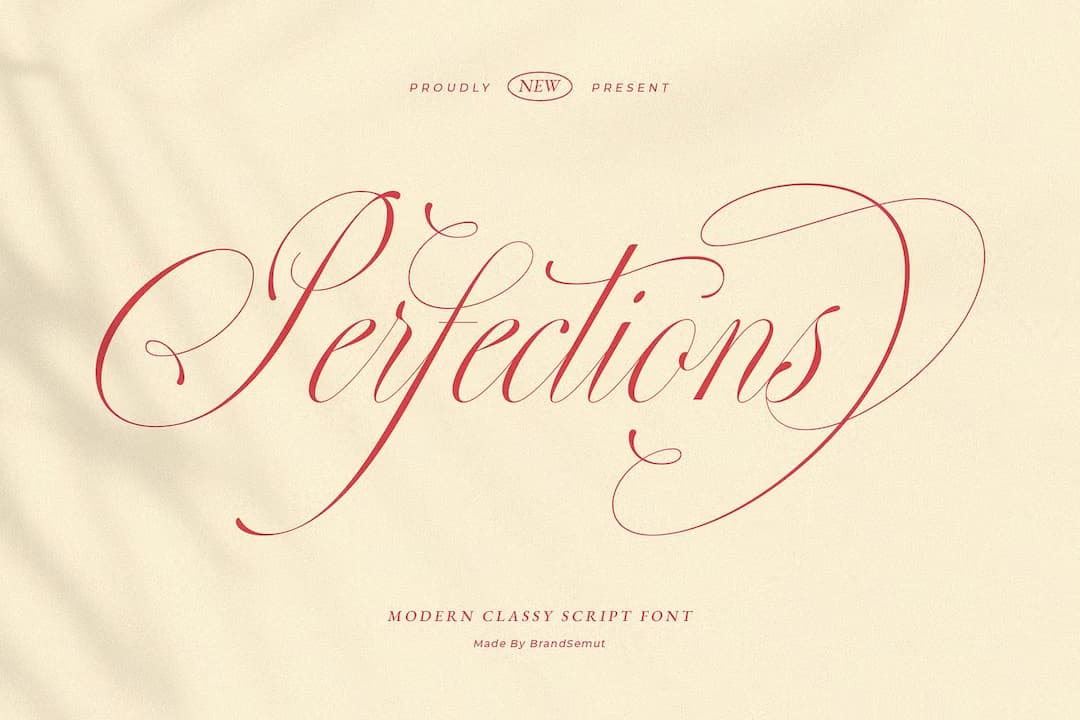
Perfections
優雅でクラシカルなカッパープレートスクリプト。伝統的なカリグラフィースクリプトだがモダナイズされており、モダンでエレガントなスワッシュオルタネートが多数ある模様。xハイトも大きく古いものに比べて読みやすくなっている。$19とかなり安いのも魅力だろう。ウェディングはもちろんバレンタインなどにもどうぞ。1ウェイト。